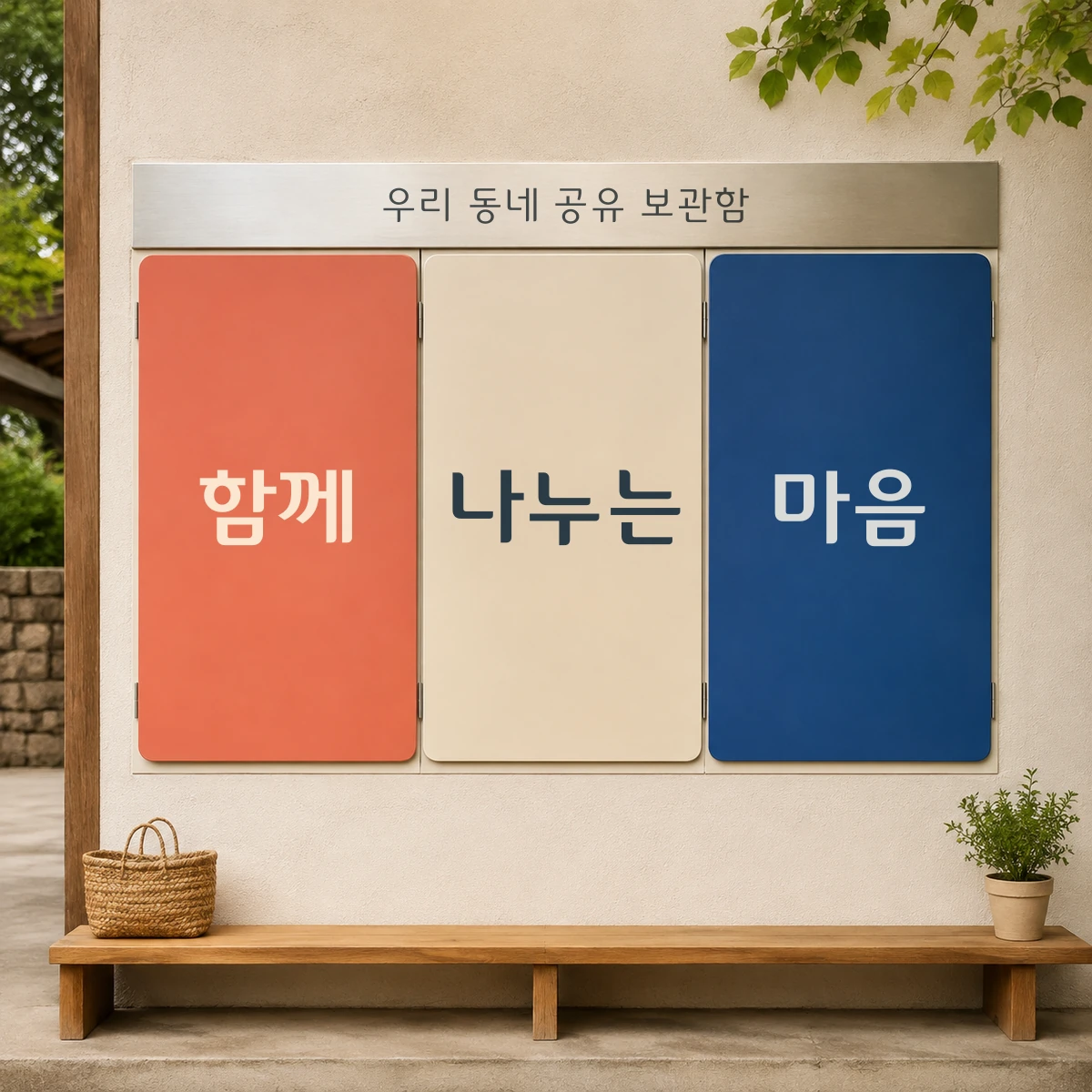
BC카드 — BC카드에서 배포하는 무료 폰트입니다. 둥근 곡선과 균형 잡힌 짜임으로 브랜드의 인상을 담아낸, 나눔의 뜻으로 공개한 디스플레이 서체
비씨카드가 2020년 7월에 무료로 공개한 서체입니다. 몇 해 동안 자사 홈페이지와 광고물에 써 오던 글꼴을 전 국민에게 푼 것으로, 공개 당시 내건 문구는 B타민 C를 나눠요였습니다. 어려운 시기에 비타민 C를 나눈다는 말장난에 서체를 나눈다는 뜻을 겹쳐 놓은 이름입니다.
제작사는 이 글꼴을 회사 심볼을 모티프로 동글동글한 느낌을 주는 제목용 글꼴이라고 설명합니다. 둥근 원형 심볼에서 형태를 가져왔다는 뜻입니다. 같은 날 함께 공개된 페이북체는 이 둥근 성질은 남기되 모바일에서 또렷하게 보이도록 직선 요소를 더한 쪽이라, 두 서체를 나란히 놓고 고르면 됩니다.
굵기는 Light와 Bold 두 가지입니다. 제작사가 스스로 제목용이라고 못 박았고 굵기도 두 단계뿐이라, 긴 본문보다는 배너와 카드 뉴스 제목처럼 짧고 굵게 읽히는 자리에 맞습니다. 모바일 화면의 작은 글자가 필요하면 페이북체 쪽이 그 목적으로 만들어졌습니다. 폰트 파일을 수정하거나 다시 배포하는 것은 금지돼 있습니다.